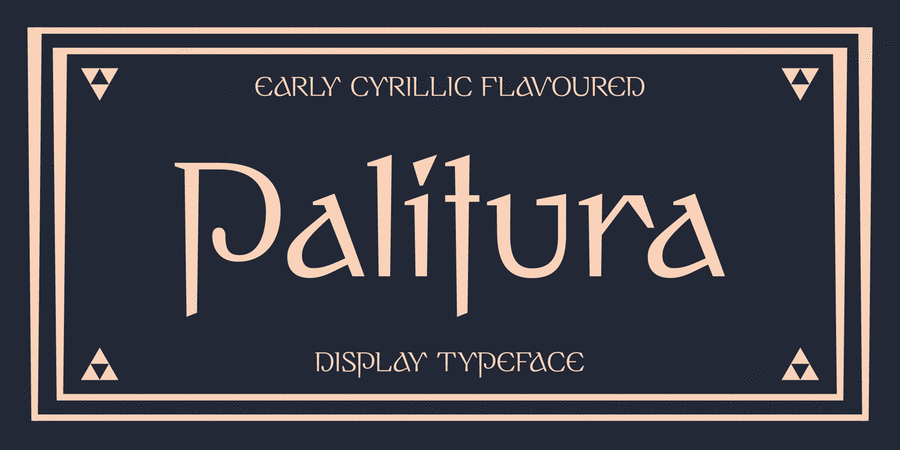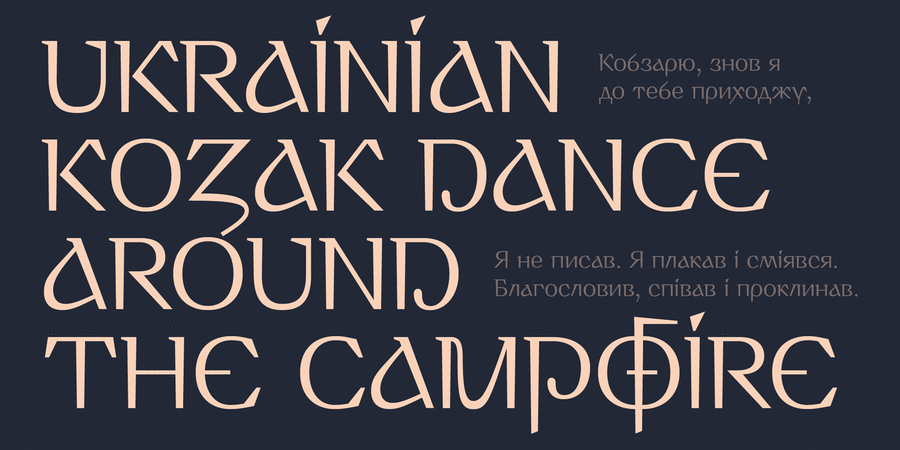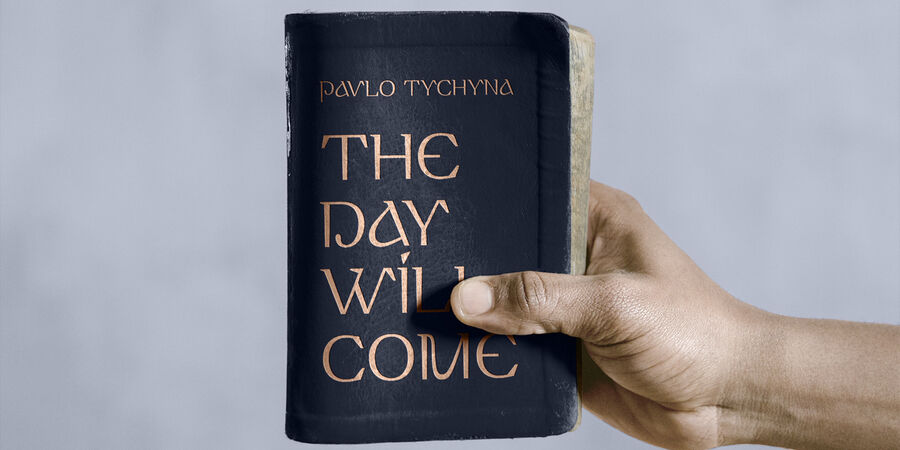
Опис гарнітури PalituraАкцидентний шрифт, розроблений для відтворення кириличного характеру в латинському письмі. Палітура (або більш сучасний вираз – палітурка) зі староукраїнської означає лакована обкладинка книги. Дизайн форми літер натхненний рукописною писемністю ранньої кирилиці (болгарська школа, XIX століття) та українськими візерунками, які передані гостротою форми, вертикальними штрихами що звужуються донизу, стилізованими косими гачками вгорі, та трикутними акцентами.
OpenType функції: локалізовані форми для азербайджанської, болгарської, каталонської, голландської, німецької, казахської, молдавської, польської, румунської, татарської, турецької; набори цифр різних пропорцій та стилів, дроби й індекси, закреселний нуль, контекстуальні альтернативи, стилістичні альтернативи.
3 писемності: латинка (включно з в’єтнамською), грецька, кирилиця (європейська + азіатська). 190 мов, 1224 символи, 1334 кернінгові пари, ручний PostScript Хінтинг.
Шрифт розробив Михайло Рафайлик у 2022 році.
Асоціації з сімейством шрифтів PalituraОсобистість і характер гарнітури:
твердий, гордий, вільний, сильний, темпераментний, мотивуючий, активний, амбітний, залізний, релігійний, історичний, екологічний, добротний, сміливий, самобутній, характерний, оригінальний, різкий, гострий, етнічний, натуральний, традиційний, колоритний, артистичний, художній, динамічний, ностальгічний, ремісничий, виразний, холодний, крижаний, консервативний, племінний, артізанальний, природний, рукотворний, героїчний, легкий, благородний, красивий, пафосний, майстерний, урочистий, епічний, дзвінкий, легендарний, прекрасний, вишуканий, фантастичний, імперський, казковий, сакральний, чіткий, жорсткий, сталевий, незвичайний, дорогий, впевнений, експериментальний, сріблястий, лицарський, аристократичний, старовинний, пивний, освічений, елітний, якісний, гуманітарний, срібний, культурний, естетичний, розкішний, дорогоцінний, унікальний, добірний, багатий, золотий, витончений, біблійний, християнський, церковний, чарівний, химерний, вигадливий, ювелірний, середньовічний, святковий, музичний, творчий, крафтовий, старомодний, королівський, тонкий, прозорий, худий, дротяний, авторитетний, переконливий, монументальний, архітектурний, кінематографічний, екстравагантний, войовничий, хоробрий, бравий, важкий, яскравий, помітний, мужній, солідний, потужний, масивний, наполегливий, дерев'яний, кам'яний, чорний, тісний
скульптура, пиво, таверна, ремесло, коваль, кіно, тату, татуювання, історія, музей, театр, алкоголь, реконструкція, фольклор, літопис, геральдика, ярмарок, хенд мейд, природа, сувенір, пам'ятник, меморіал, вишиванка, етнографія, замок, легенда, література, епос, прикраса, ювелір, надгробок, мистецтво, пригоди, фентезі, Чарівна казка, казка, Біблія, мода, одяг, розкіш, архітектура, годинник, ресторан, лицар, обладунки, меч, антикваріат, паб, Трофей, нагорода, бібліотека, музика, вино, срібло, художник, преміум, шоколад, коштовності, сервіровка, віскі, туризм, банкнота, золото, монета, бутік, сувій, мініатюра, чарівник, король, дракон, кузня, кафе, магія, свято, Christmas, кухня, сир, церква, храм, монастир, релігія, ікона, графіка, ілюстрація, захід сонця, люкс, мед, меню, вечір, комп'ютерна гра, фарби, зброя, прапор, взуття, шолом, хліб, м'ясо, свічки, пряник, бій, камінь, граніт Гарнітура асоціюється з віком: